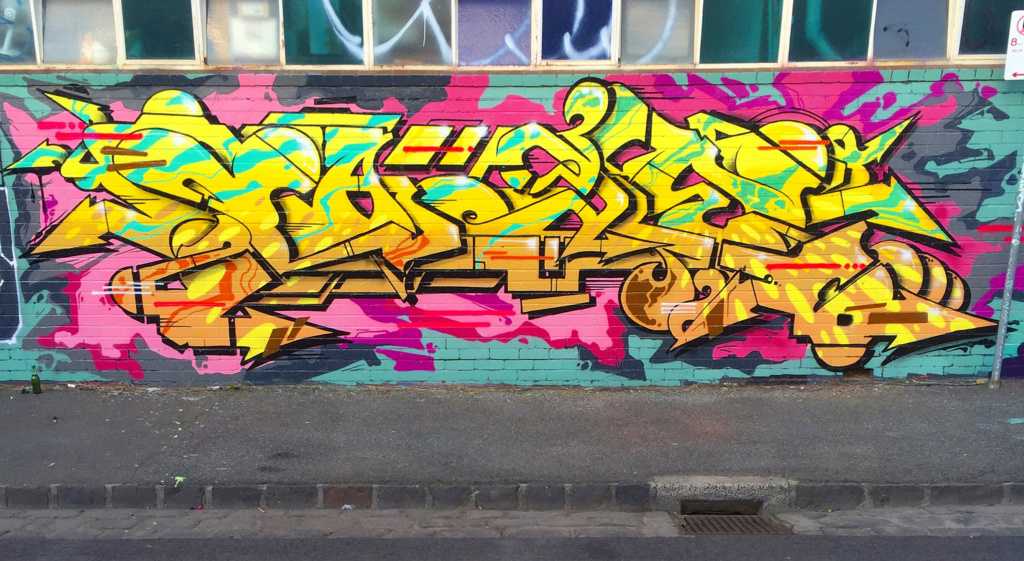
Создай граффити текст в Фотошоп — Работа с текстом — Photoshop — Каталог статей
Для урока нам понадобится кисть Star Brushes.
Шаг 1 — Создание нового документа
Создаем новый документ размером 1000х500 пикселей. Вы можете сделать это через меню File — New (Файл — Новый).
Шаг 2. Активируем фоновый слой и используем Paint Bucket Tool (Заливка) (G), чтобы залить его цветом #D0CFCF.
Шаг 3 — Текст
Для текста создаем новый слой, вы можете найти в интернете подходящий шрифт или нарисовать четкий контур букв на бумаге, отсканировать и импортировать его в Фотошоп. Далее берем Pen Tool (Перо) (Р) и создаем контур одной из букв. Я использовала слово «Graffiti».
Шаг 4. Преобразовываем контур в выделение, кликнув по нему правой кнопкой мыши и выбрав Make Selection (Создать выделение), заливаем его любым цветом.
Шаг 5. Переименовываем этот слой. Я назвала его просто «G». Дублируем (CTRL+J) его и располагаем под оригиналом. Дважды кликаем по слою «G копия», чтобы вызвать окно Layer Style (Стиль слоя) и изменить цвет.
Шаг 6. Затем перемещаем слой «G копия» на 5 пикселей вверх и 8-9 вправо, используя клавишы со стрелками.
Шаг 7. На слое «G» добавляем стили слоя. Начнем с Inner Shadow (Внутренняя тень).
Шаг 8. Вот так должен выглядеть ваш результат. Переходим на слой «G копия», затем Layer — Layer Style — Create Layer (Слой — Стиль слоя — Создать слой). БеремBurn Tool (Затемнитель) (O) и затемняем отмеченные области. Закончив, беремDodge Tool (Осветлитель) (О) и осветляем отмеченные области.
Зелеными окружностями отмечены места, где я использовала Burn Tool (Затемнитель) (О), красными — Dodge Tool (Осветлитель) (О).
Шаг 9. На слое «G копия» добавляем стиль слоя Drop Shadow (Тень).
Шаг 10. Создаем новый слой, загружаем выделение слоя «G копия» (зажав CTRL, кликаем по миниатюре слоя на панели слоев) и применяем Edit — Stroke (Редактирование — Обводка). Располагаем обводку под слоем «G копия».
Шаг 11. Создаем новый слой и называем его «Прямоугольники», берем инструмент выделения и создаем несколько прямоугольных фигур, залитых цветом #8cb809.
Шаг 12. Теперь мы добавим блик. Создаем новый слой и с помощью Pen Tool (Перо) (Р) рисуем блик, как показано ниже. Заливаем его цветом #FFFFFF.
Шаг 13.
Стираем лишнюю часть. Для этого выделяем слои «G» и «G копия» (зажав CTRL+ALT, кликаем по миниатюре слоя на панели слоев). Далее Select — Inverse(Выделение — Инвертировать) и удаляем лишнюю часть слоя с бликом клавишей Delete.
Шаг 14. Меняем режим смешивания слоя с бликом на Soft Light (Мягкий свет) и добавляем стиль слоя Layer — Layer Style — Inner Shadow (Слой — Стиль слоя — Внутренняя тень).
Шаг 15. Повторяем все шаги для остальных букв.
Шаг 16 — Облака
Создаем новый слой и называем его «Облака». Располагаем его под слоями с буквами. Берем Brush Tool (Кисть) (В) и, регулируя диаметр рисуем много окружностей, придав им вид облака.
Я использовала цвет #e40480. Закончив, дублируем (CTRL+J) этот слой.
Шаг 17. Добавляем стили слоя к оригиналу слоя «Облака» Layer — Layer Style — Bevel and Emboss (Слой — Стиль слоя — Фаска и Тиснение).
Шаг 18. Вот так должна выглядеть иллюстрация на данном этапе.
Шаг 19. Создаем новый слой над слоем с облаками и мягкой круглой кистью (В) белого цвета рисуем блики на облаке. Непрозрачность кисти должна быть очень низкой.
Шаг 20. Переходим к слою «Облака копия» и переносим его под оригинал, затем меняем opacity (непрозрачность) на 27%. Слегка сдвигаем этот слой в сторону, чтобы создать тень.
Шаг 21. Создаем новый слой, берем жесткую круглую кисть (В) и, регулируя диаметр, создаем новые облака.
Я использовала цвет #8cb809.
Шаг 22. Добавляем стили слоя.
Шаг 23. Создаем новый слой и добавляем немного сияния облакам с помощью маленькой мягкой кисти (В). Я использовала Smudge Tool (Палец), чтобы растянуть блики.
Шаг 24. Теперь я покажу вам, как создать фон. Сначала создаем новый документ.
Шаг 25. Берем инструмент Rounded Rectangle Tool (Закругленный прямоугольник) (U) и создаем прямоугольник. Я использовала цвет #8cb809 и радиус 21 px.
Шаг 26. Добавляем стиль слоя Stroke (Обводка).
Шаг 27. Дублируем прямоугольник и располагаем копии так, чтобы создать кирпичную кладку. Обратите внимание, что каждый нижний кирпич немного перекрывает верхний и белого фона не видно.![]()
Шаг 28. Создаем новый слой над кирпичами и мягкой круглой кистью диаметром 60 px и цветом #000000 рисуем тени на кирпичах. Меняем непрозрачность слоя на 27%.
Шаг 29. Переходим Edit — Define Pattern (Редактировать — Определить узор), в появившемся окне вводим имя и жмем OK. Возвращаемся к документу с граффити. Создаем новый слой под слоем с облаками. Заливаем его цветом #FFFFFF и уменьшаем fill (заливка) до 0%. Добавляем стили слоя.
Шаг 30. Создаем новый документ и на некоторых кирпичах добавляем блики. Я использовала мягкую круглую кисть (B) и Smudge Tool (Палец), чтобы размазать их.
Шаг 31. Теперь займемся световыми лучами. Создаем новый слой над текстом и активируем Brush Tool (Кисть) (В), устанавливаем размер на 87 px.